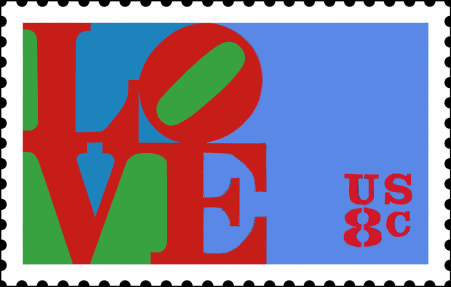
Love-Schrift identifizieren
Und ich habe auch gleich schon eine Frage:
Wisst Ihr, was das für eine Schrift ist?
Oder könnt Ihr mir Tipps geben, welche Bücher/Sites geeignet sind, um dies herauszufinden?
Hast Du vielleicht aber schon einen heißen Tipp?
Wisst Ihr, was das für eine Schrift ist?
Die Buchstaben sind sicherlich eigenständig entwickelt worden. Grundlage war eine klassizistische Antiqua, ähnlich der „Bodoni Poster“. Aber die Serifen passen nicht so ganz. Diese haben einen runden Übergang. Sehr nahe dran ist IMHO die „Sahara Bodoni“.
Noch ein paar Infos zum Werk selbst …
Die verschiedenen Versionen auf Briefmarke und als Skulptur unterscheiden sich aber etwas. Die Form des O in der Skulptur ist in meinen Augen eindeutig klassizistisch. Bei der Skulptur gehe ich daher weiterhin von handgeblasenen und mundgedengelten Buchstaben, auf der Basis einer fetten, klassizistischen Antiqua mit modifizierten Serifen, aus. Ein echter Typonerd wird für so eine Skulptur IMHO nicht auf eine Schrift aus der Konserve zurückgreifen. Wenn man schon so eine große Skulptur baut kann man durchaus auch noch etwas Zeit für das Konstruieren von 4 Buchstaben investieren, denn das harte Künstlerleben bietet den Kreativen ja sonst nicht viele Freuden. Es handelt sich hier um eine echte Profiarbeit, nicht um eine Arbeit aus einem Grundkurs Design des GK Bildende Kunst im 8jährigen Abi. Im letzteren Fall würde ich von einer Instantschrift aus der Tüte ausgehen.
ein solcher "Typonerd" war, dass er ein Schriftmusterbuch beim Arbeiten danebenliegen hatte oder gar die Schrift konstruiert hätte. Die Ausgangsbasis bzw. der Ursprung all der Love-Variationen war meines Wissens eine Serie von Ölgemälden, der ganze andere Kladderadatsch mit Siebdruck, Postkarte, Skulptur, Briefmarke, T-Shirt und weiß Gott noch was entstand danach und war eigentlich nur Vermarktungs- und Verwertungsmaschine. Indiana hat solche Clarendon-Typen auch in vielen seiner anderen Arbeiten gern benutzt: vermutlich weil das sehr amerikanische (Western), damals sehr oft in Reklame verwendete und obendrein zu seiner an Werbeschilder und Signets orientierter Bildsprache gut passende Schriften waren, die den Raum relativ gleichgewichtig ausfüllen. Es gibt in Indianas Arbeiten verschieden "verzerrte" Clarendons: breitere und schmalere, aufs Quadrat getrimmte Einzelbuchstaben usw.
Diese so abgewandelten Clarendons waren also vor allem aus inhaltlichen Gründen (welche andere Schrift könnte schon amerikanischer sein?) und praktischen (es gibt ja kaum eine andere, die man so unbeschadet verschiedenen Räumen anpassen kann und obendrein ist sie immer gleichstark im Raum und außerdem relativ leicht zu malen) die Schriften seiner Wahl. Für Feinheiten der Schriftgeschichte hat sich Indiana nach meinen Kenntnissen gar nicht interessiert - er begriff sich als Künstler und gebrauchte die Mittel des Schildermalers um "Marken" (oder vielleicht besser "Zeichen") zu malen. Hochinteressante Sachen, die aber - wenn man sich mit dem Lebenswerk von Indiana beschäftigt - auf Dauer dann doch halt in einer im Grunde vermutlich wenig weiterentwicklungsfähigen "Masche" enden.